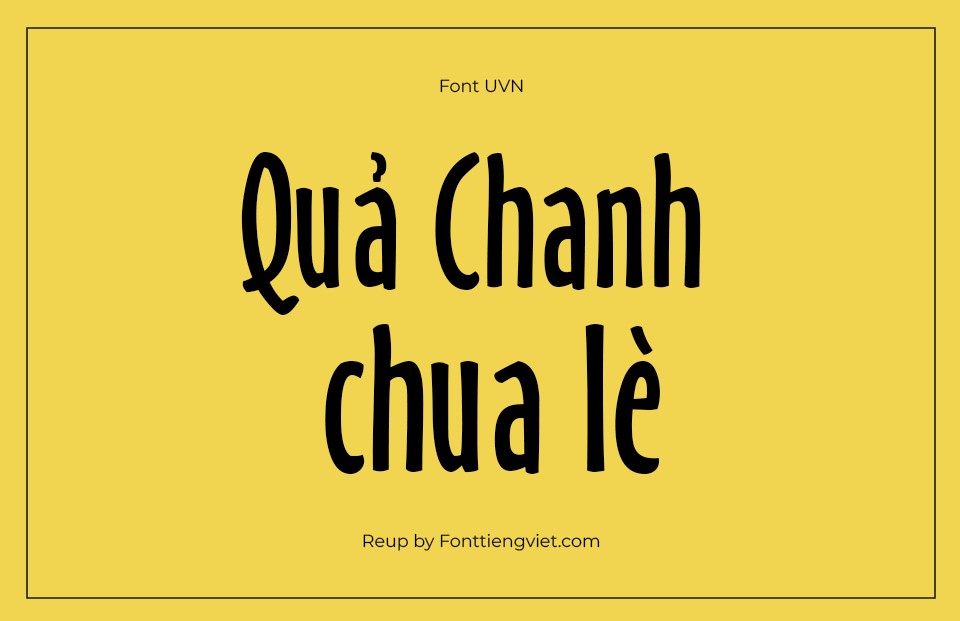
Font Việt Hóa UVN Ban Tay
Font Việt Hóa UVN Ban Tay – Bộ Font Chữ Viết Tay Tuyệt Đẹp Cho Học Đường
Giới thiệu về Font Việt Hóa UVN Ban Tay
Trong thế giới thiết kế đồ họa giáo dục, việc lựa chọn một Font Miễn Phí có phong cách gần gũi luôn là ưu tiên hàng đầu. Font Việt Hóa UVN Ban Tay là một trong những bộ phông chữ mô phỏng nét chữ viết tay tự nhiên một cách chân thực nhất. Được phát triển dựa trên bảng mã Unicode chuẩn, bộ font này giúp người dùng dễ dàng soạn thảo văn bản tiếng Việt mà không lo lỗi font hay thiếu ký tự. Với đường nét mềm mại và uyển chuyển, nó mang lại cảm giác thân thiện, phù hợp cho các bài giảng điện tử hoặc tài liệu học tập dành cho học sinh.
Ưu điểm nổi bật của Font Việt Hóa UVN Ban Tay
Phong cách thiết kế tự nhiên
Điểm đặc biệt của Font Việt Hóa UVN Ban Tay chính là sự mộc mạc và tinh tế. Mỗi chữ cái được tạo hình như được viết bằng bút mực trên giấy, tạo nên sự kết nối cảm xúc giữa người viết và người đọc. Đây là lựa chọn hoàn hảo để làm tiêu đề báo tường, thiệp mời hoặc các nhãn vở thủ công.
Tính ứng dụng cao trong học đường
Không chỉ dừng lại ở tính thẩm mỹ, bộ font này còn có độ giãn cách ký tự hợp lý, giúp văn bản dễ nhìn và dễ đọc. Các giáo viên có thể sử dụng Font Việt Hóa UVN Ban Tay để thiết kế slide thuyết trình sinh động, giúp học sinh hứng thú hơn trong tiết học. Sự tương thích tốt trên các phần mềm như Word, PowerPoint hay Photoshop là một điểm cộng lớn.
Kết luận và cách sử dụng hiệu quả